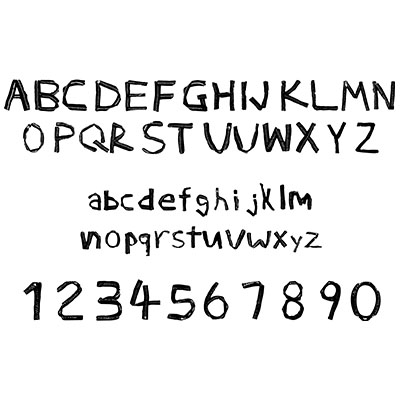
ジグザグフォント
ジグザグで話す!
布にミシンをかけるのが大変でした。 その後アルファベットを鉛筆で描きました。 そのアルファベットの形に布貼りました。 布を切ったり 針金を入れたり 貼ったりするのは、みんなでやりました。時間がかかって大変でした。(モエ)
各文字が少しずつ異なる形をしているため、動きと遊び心が感じられます。このフォントは、カジュアルでリラックスした雰囲気を求めるデザインに最適です。例えば、子供向けの絵本やポスター、カフェのメニュー、または手作り感を出したいイベントの案内状などにぴったりです。手書きの温かみと親しみやすさを活かし、多様な用途で使える素晴らしいフォントです。(Saiyan)
アトリエ福花の得意分野でもある、布とミシンを使ってのフォントができました。黒い布にジグザグミシンをかけて細くカットしました。更に針金を入れて文字のカタチを作りました。布の質感とステッチを楽しめるフォントとなりました。ファッション関係のデザインに使っていただけたら嬉しいです。(渋谷アトリエ福花)